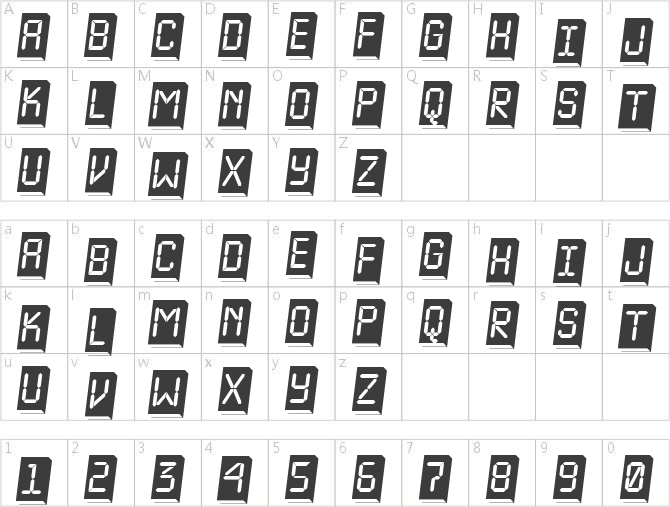
a_LCDNova3DPlObl 詳情頁(yè)
a_LCDNova3DPlObl字體字庫(kù)是一款讓人賞心悅目、百看不厭的英文字體,適合各類廣告和產(chǎn)品包裝設(shè)計(jì)應(yīng)用,字體大小0.04MB,格式為ttf字體,上傳用戶是……西央,作者/版權(quán)方為未知